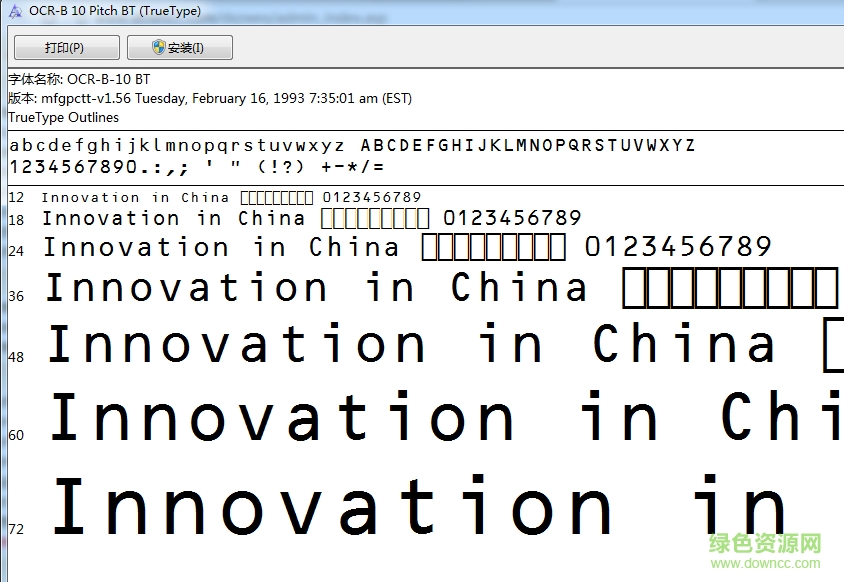
OCR-B 10 BT字體是商品條形碼和身份證號(hào)的數(shù)字字體及PS的最佳伴侶,這款字體的效果和身份證號(hào)上的字體是一樣的,用戶能夠通過使用這款字體打出非常標(biāo)準(zhǔn)的數(shù)字來,在平時(shí)的商品條形碼中也是經(jīng)常用到。需要的朋友就趕快來綠色資源網(wǎng)下載使用吧!
OCR-B 10 BT是一款常用的條形碼字體,如果缺少這款字體,就可能導(dǎo)致條形碼無法正常打印,小編為您帶來free3of9免費(fèi)字體下載,歡迎來本站下載使用。